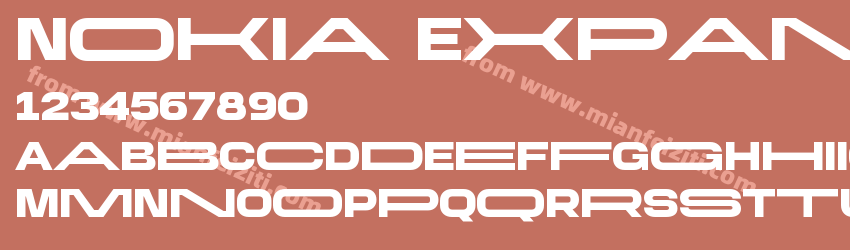
Nokia Expanded Extra Bold
字体名称: Nokia Expanded Extra Bold
Postscript名称: NokiaExpanded-ExtraBold
本款“Nokia Expanded Extra Bold”是一款书写很新颖的字体,字体大方,适合各种设计作品使用!欢迎下载!